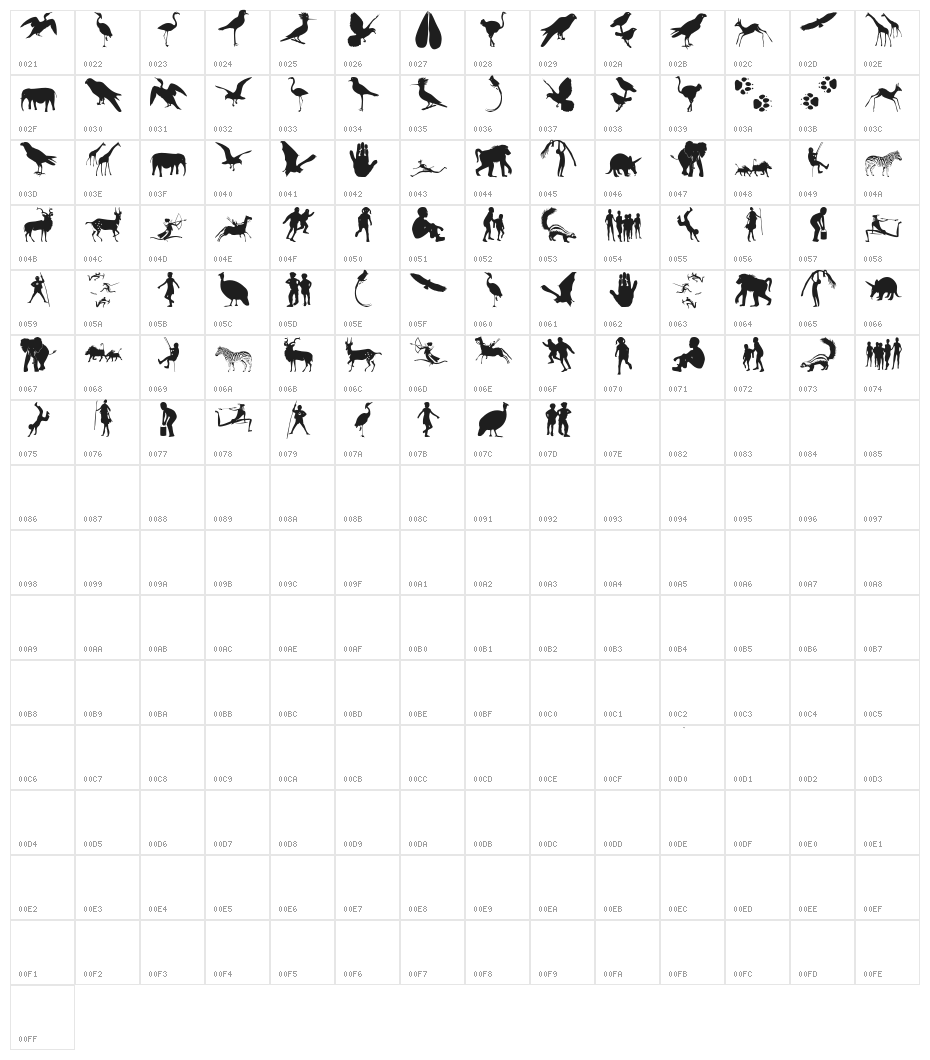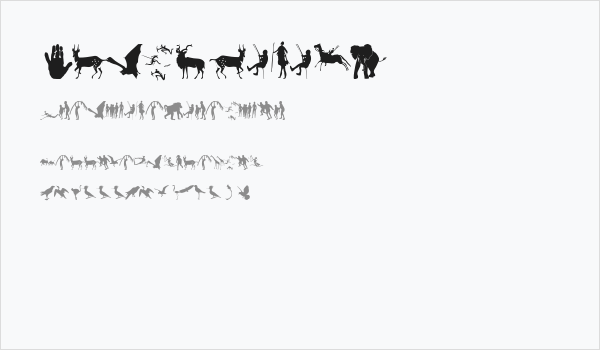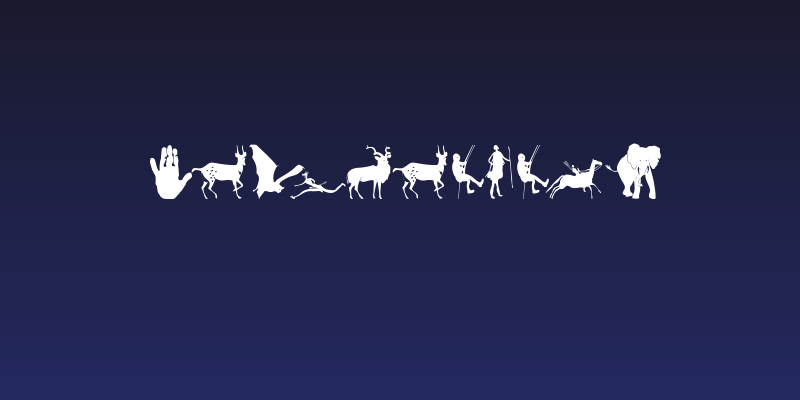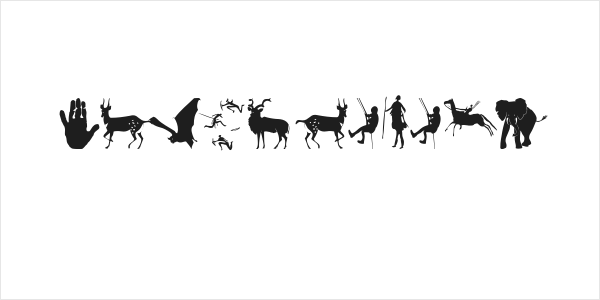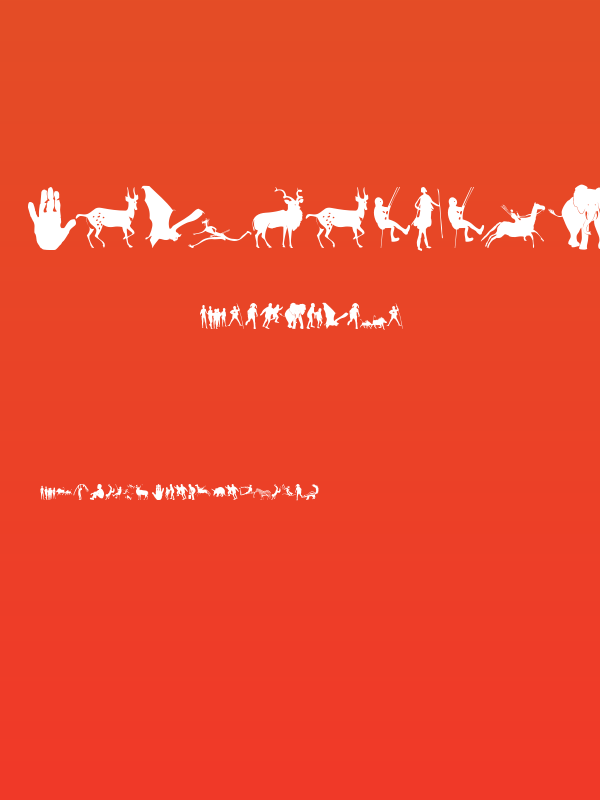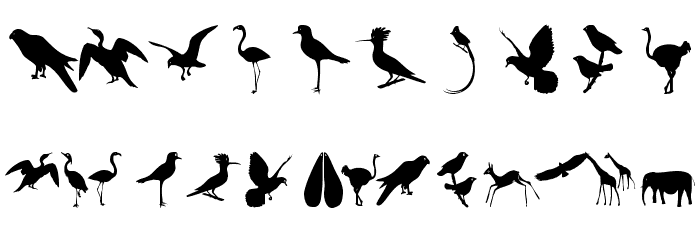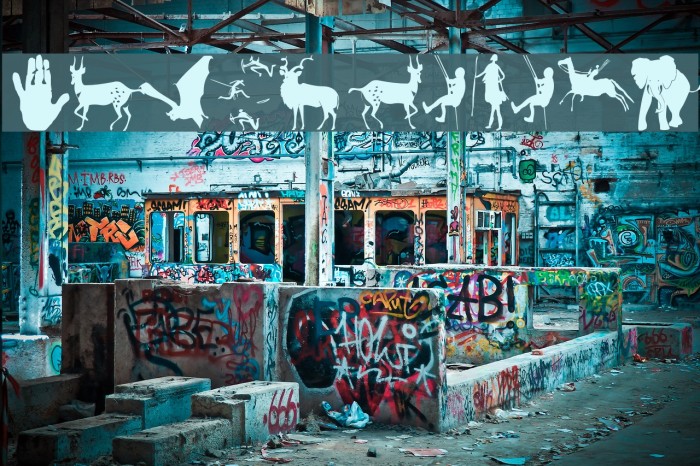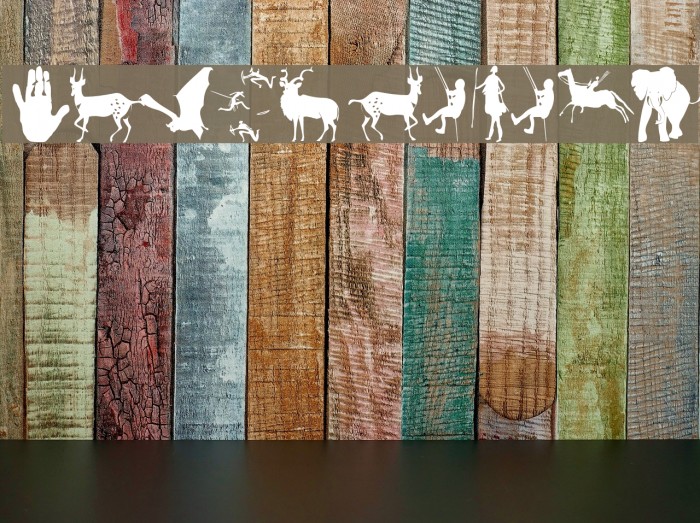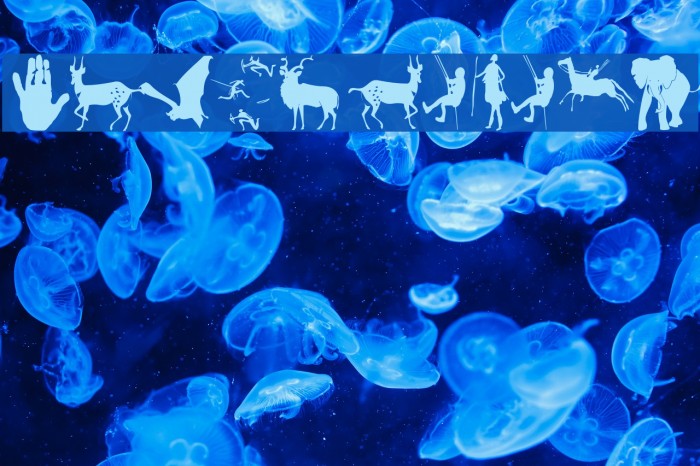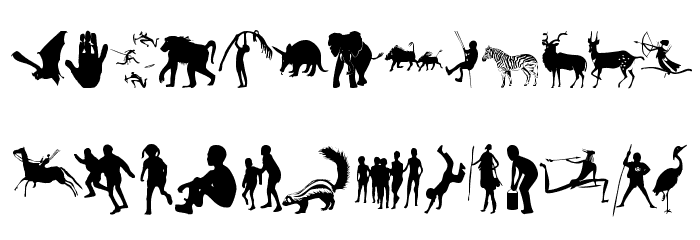
BlackLiving Font
| Stile generale | Decorative, Playful, Organic |
| Caso d'uso | Headlines, Posters, Logos, Themed Graphics |
| Progetti proposti | Children’s books, educational posters, wildlife campaigns, creative branding, event invitations, themed signage. |